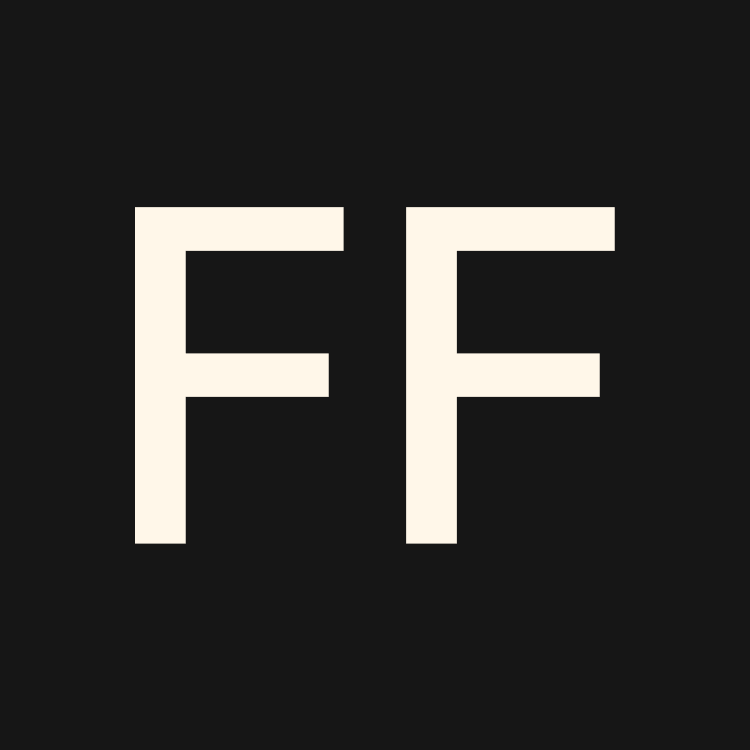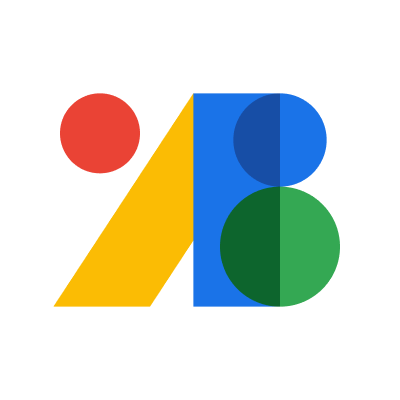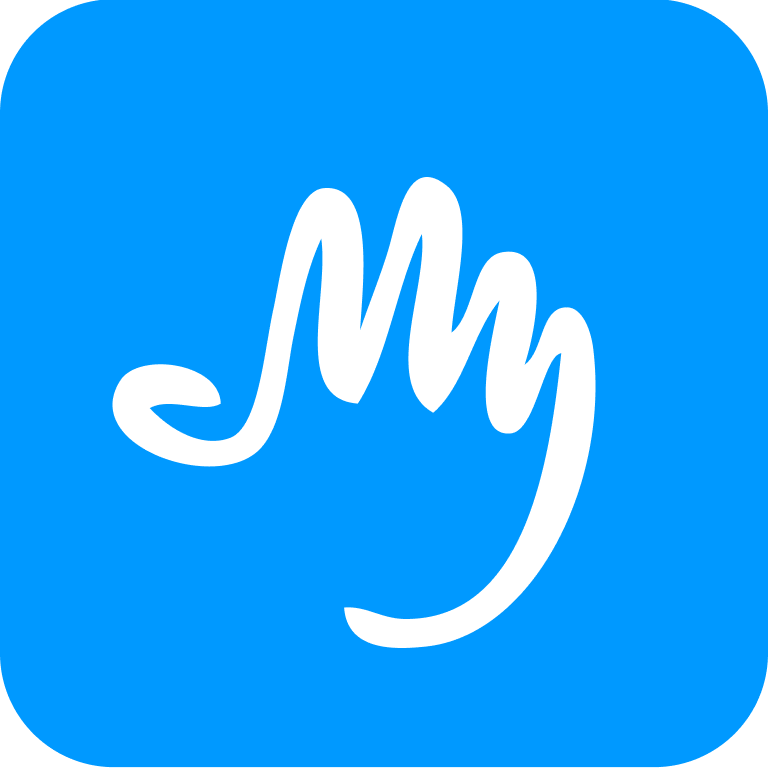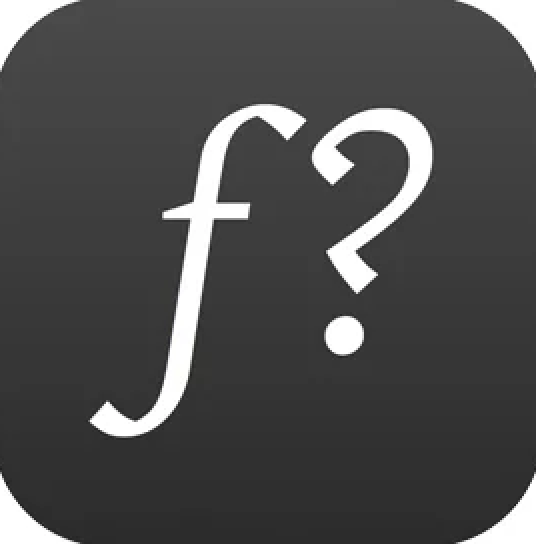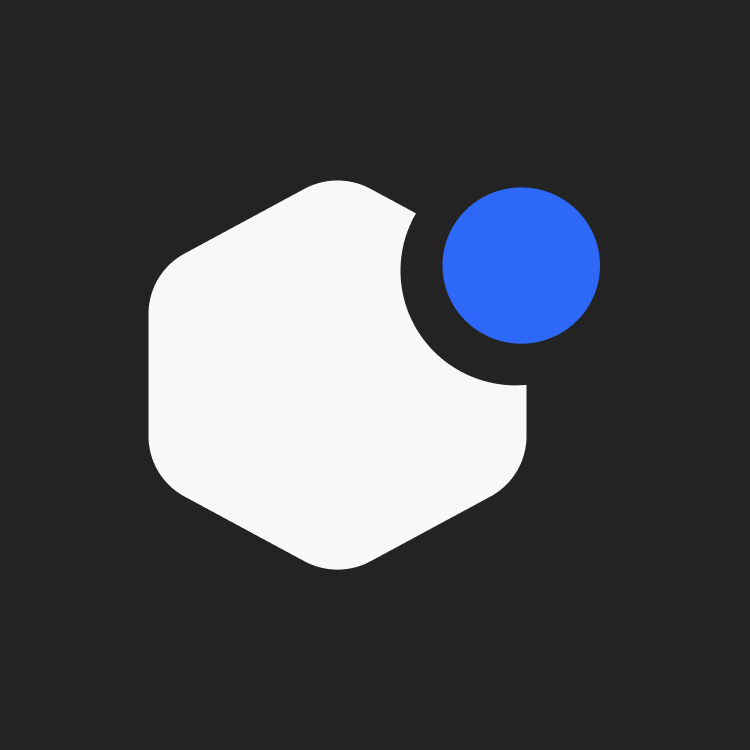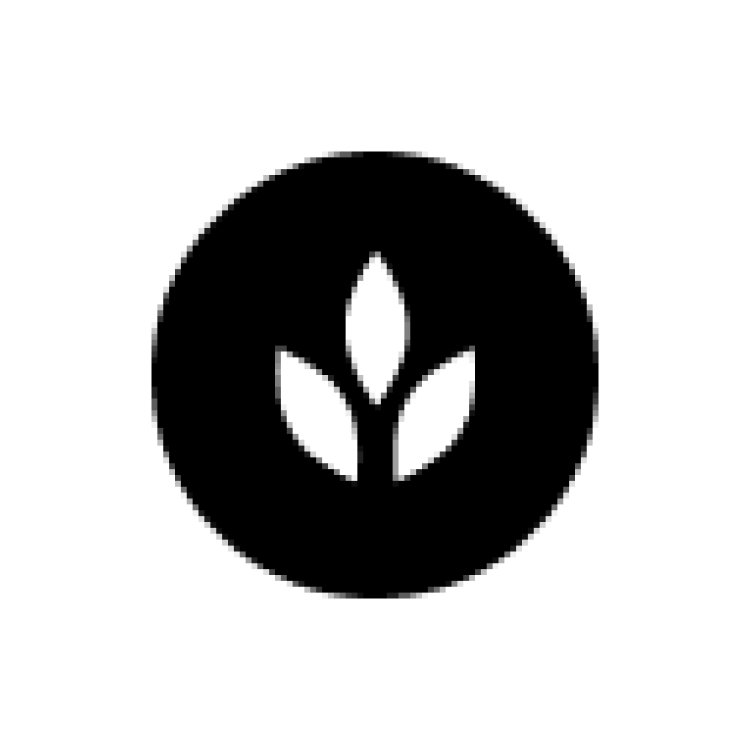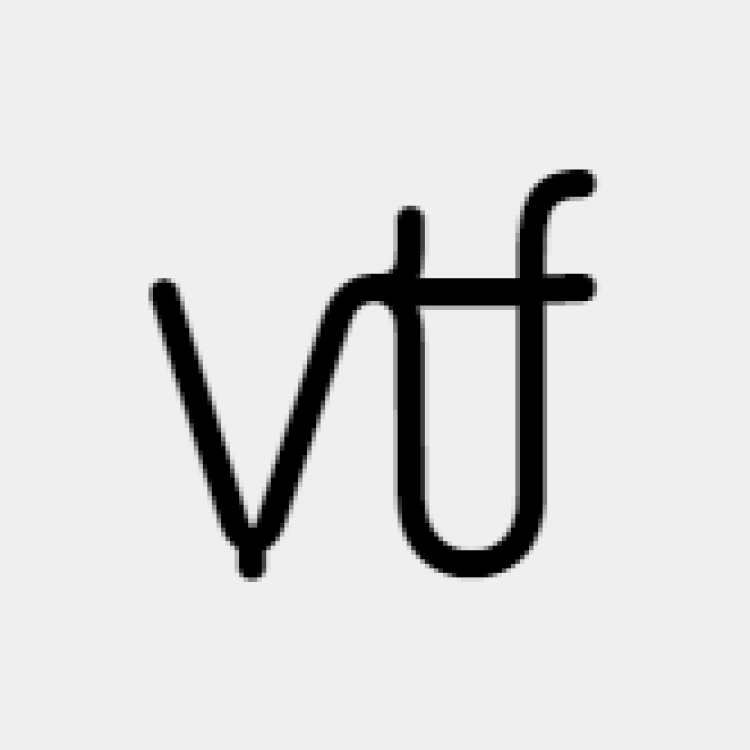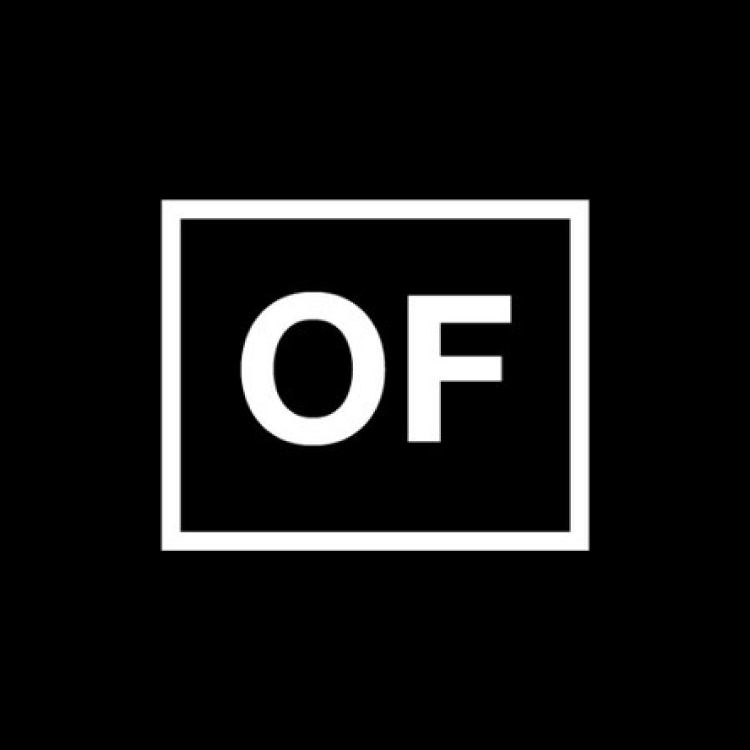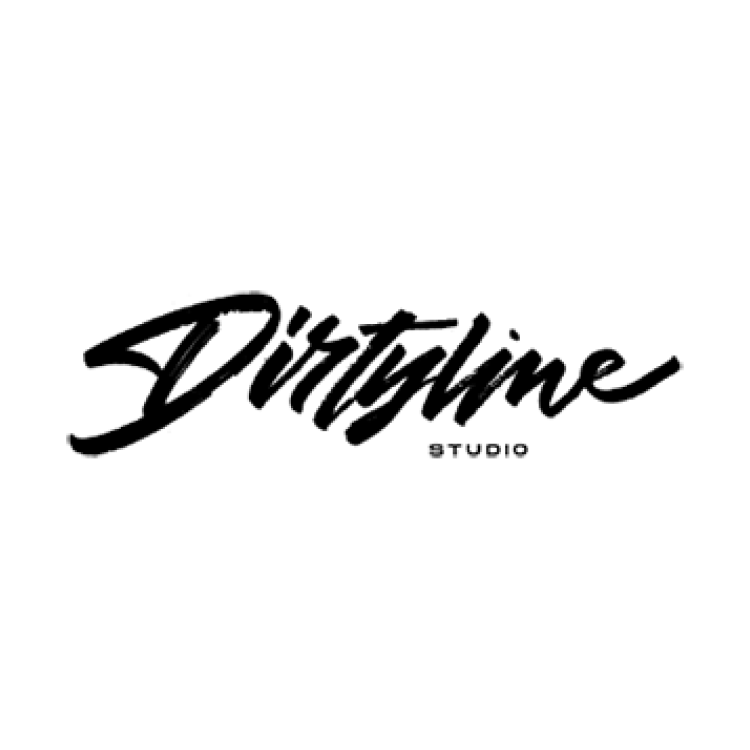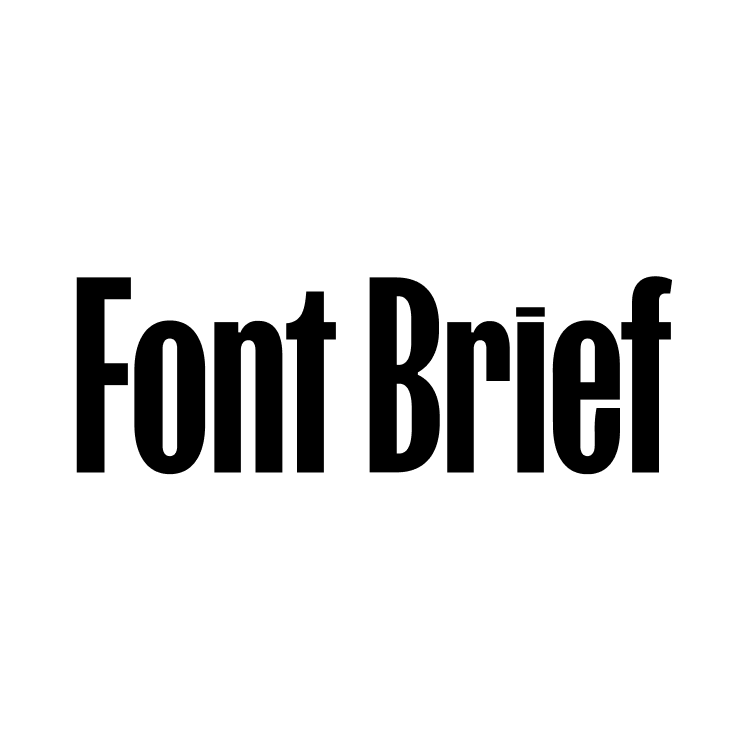
Сервисы, которые помогут найти крутой шрифт для проекта
Free faces
Бесплатные креативные шрифты.
FontBrief
Сервис позволяет подобрать шрифты по описанному вами настроению.
Naga
Бесплатный шрифт с засечками.
Dirty Line Studio
Различные креативные шрифты как платные, так и бесплатные.
New Gerbil Modern Sans
Бесплатный шрифт.
Open-foundry
Бесплатные шрифты.
Velvetyne
Бесплатные шрифты.
Google Fonts
Библиотека с более чем 1000 шрифтов, которые имеют свободную лицензию.
WhatFont
Расширения для браузера, которое позволяет узнать, какие шрифты используются на сайте
MyFonts
Мощный поисковик шрифтов на основе AI с огромной библиотекой и возможностью купить найденный шрифт.